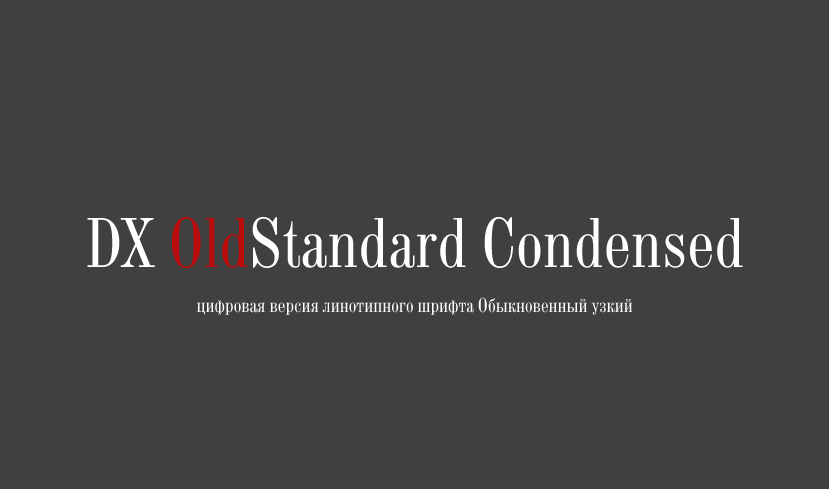
Шрифт Обыкновенный узкий/DXOldStandardCondensed
Выпущен шрифт DXOldStandardCondensed, линотипной шрифтовой пары «Узкая антиква+Гротеск» начала XX века. Шрифт использовался для набора в 9 и 10 кеглях. Гарнитура состоит из двух начертаний: исторического Обыкновенного узкого No1 и Обыкновенного узкого No2 с альтернативными знаками цифр.